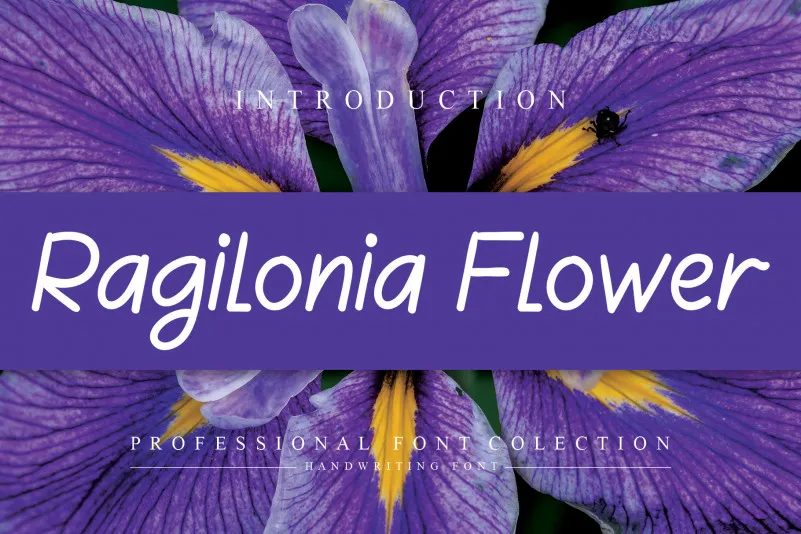
A Fonte ‘Ragilonia Flower Handwritten’ oferece uma experiência visual agradável e sofisticada que se destaca em qualquer projeto de design. Com suas letras delicadas e curvilíneas, essa fonte é perfeita para dar um toque especial a uma ampla gama de aplicações, desde o branding até as identidades digitais, nomes de eventos, anúncios pessoais, selos, logotipos e mais. Seja em um evento de casamento elegante ou no desenvolvimento de um novo projeto gráfico, essa fonte vai tornar seu trabalho de design ainda mais profissional e encantador. É uma escolha ótima para aqueles que buscam uma fonte delicada capaz de destacar seus designs sem deixá-los aparentemente fracos.